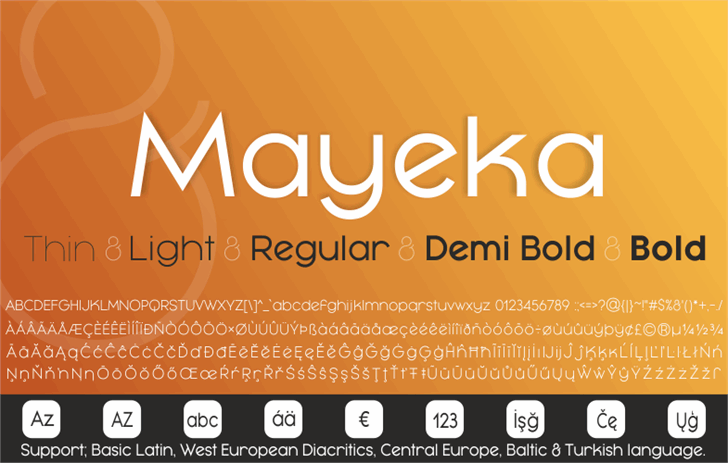
A Mayeka Typeface é uma elegante escolha para projetos digitais que valorizam uma aparência clean e moderna. Essa fonte sans serif apresenta linhas finas, leves e fluidas, que criam um equilíbrio suave entre seriedade e sofisticação. Perfeita para textos de negócios ou design gráfico contemporâneo, a Mayeka traz uma dinâmica única capaz de destacar seu conteúdo sem perder o foco no leitor. Para aqueles que estão curiosos sobre os detalhes dessa fonte tão versátil e moderna, visitar o site do designer Studiotypo é uma ótima opção para explorar mais. Não esqueça de acessar a página dedicada aos testes de visual da Mayeka em sua plataforma, onde você pode experimentar diferentes configurações e aplicá-las ao seu design.
Designer: Studiotypo